前回は簡略化した赤入れとしてW-とW+の紹介をしました。今回ももう少しアルファベットの赤入れを紹介していきます。
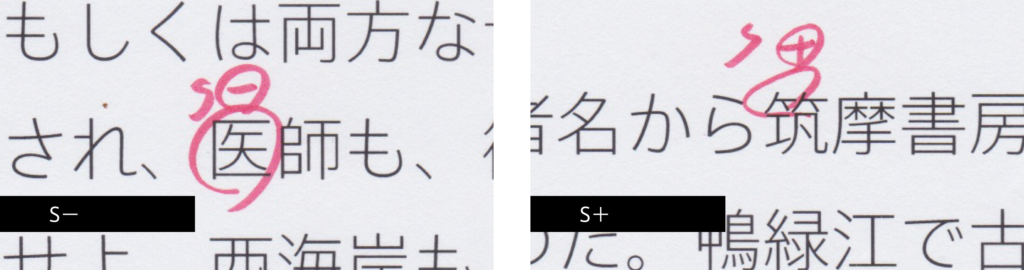
Sはサイズの意味で、S-なら「小さく」、S+なら「大きく」という指示です。単純に拡大縮小すると筆画の太さもいっしょに変わってしまうので、太さは変えずに骨格を小さくしたり大きくしたりするようなイメージで修正します。
「医」は文字全体を小さくという指示です。四角い文字は字面いっぱいに作ると他の文字より大きく見えがちなので、サイズ調整で気を使います。「筑」は竹冠の左の部分だけを大きくという指示です。竹冠は左右のバランスもチェックします。
Cはカウンターの意味です。C-なら「カウンターを狭く」、 C+なら「カウンターを広く」となります。ここでは「古」の「口」の部分のカウンターを狭くするよう指示が入っています。TPスカイシリーズの赤入れではC+よりC-をよく見ました。
他にも、「G」で重心の上げ下げを指示したりします。